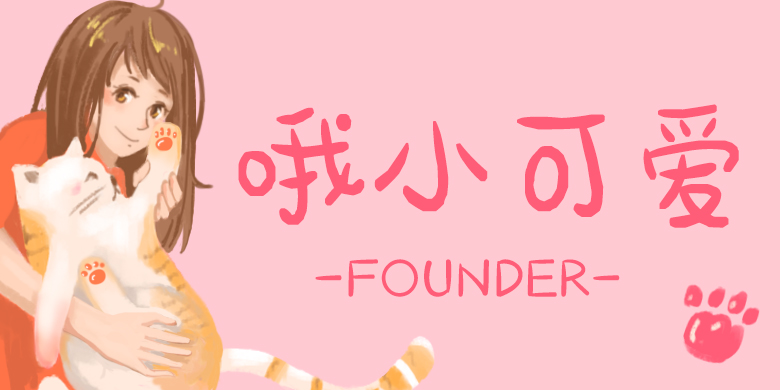
方正手迹-哦小可爱 简
方正手迹-哦小可爱
品牌: 方正手迹
设计师: 余丹
发行时间:2019
分类:创意字体
字体介绍:
方正手迹-哦小可爱,富有意趣的笔画,生动多变的结构,可爱的气质拿捏的恰到好处。同时采用较大的中宫,增加字面,具有良好的页面展示效果。适用于少儿类书刊,及现代诗歌、短文的排版以及文化、商业类品牌的广告语设计。